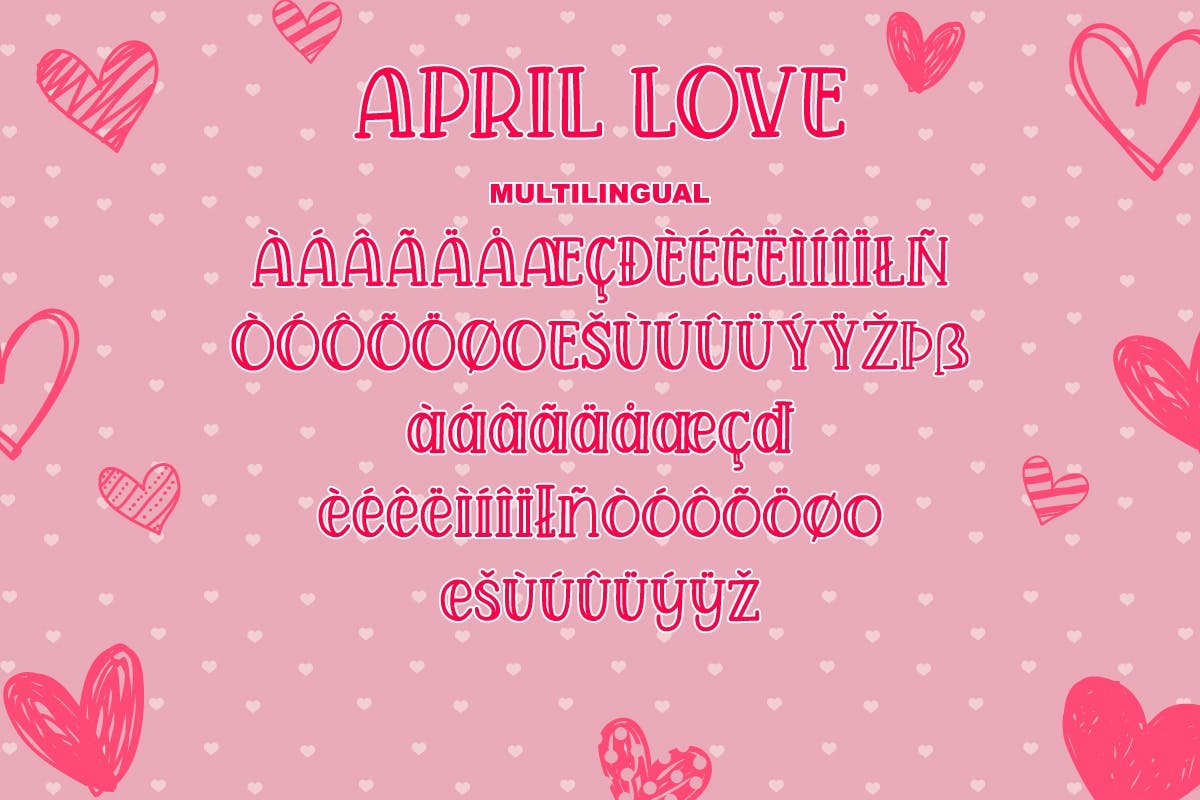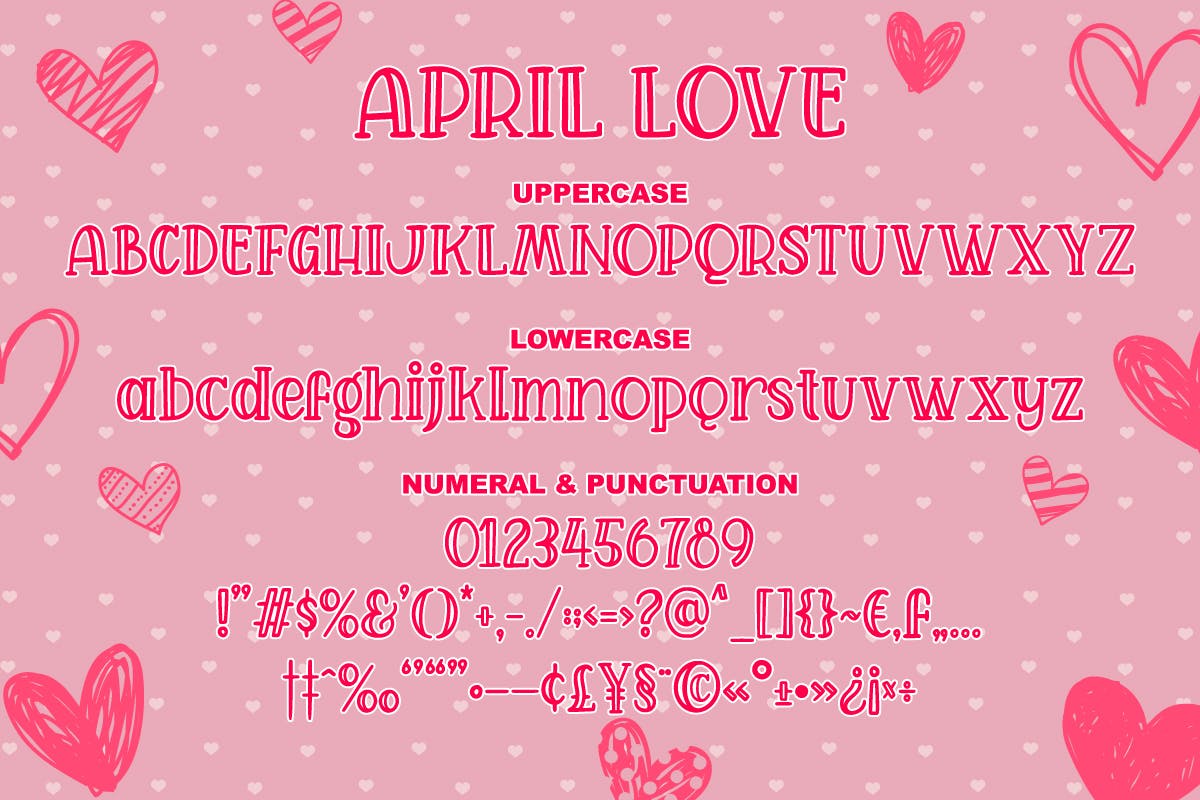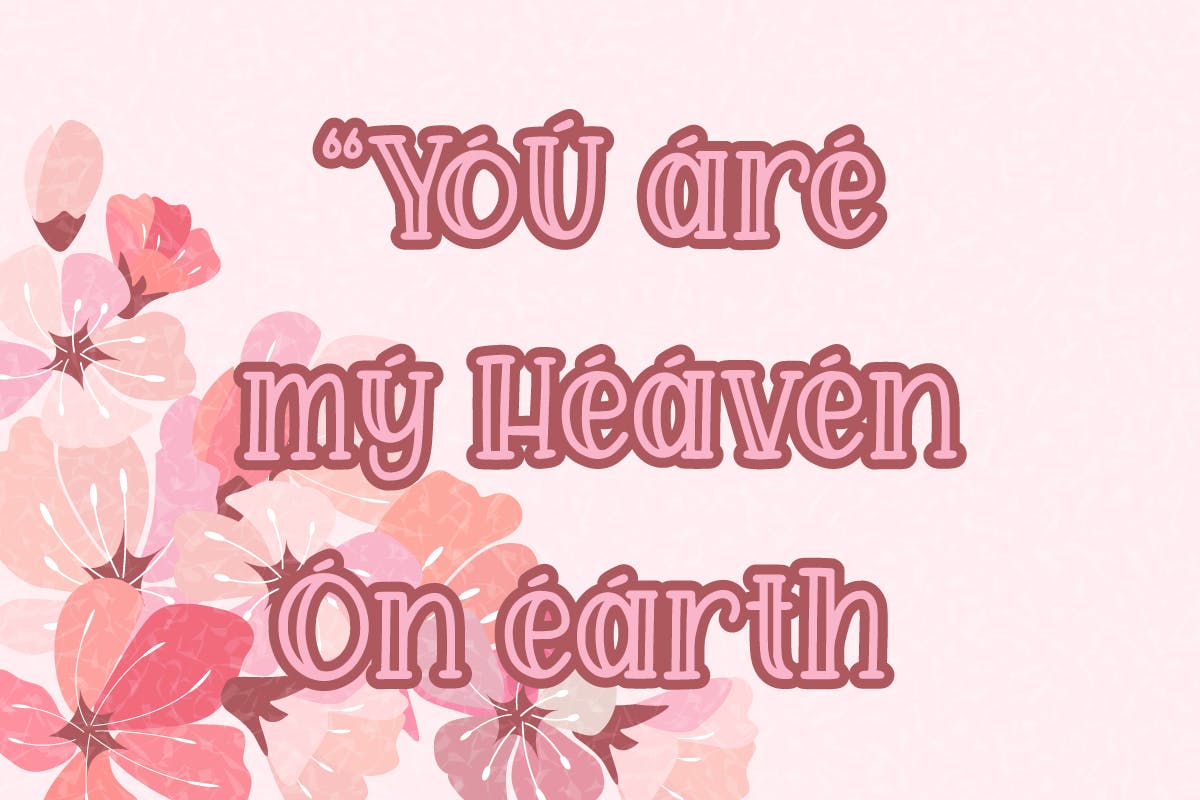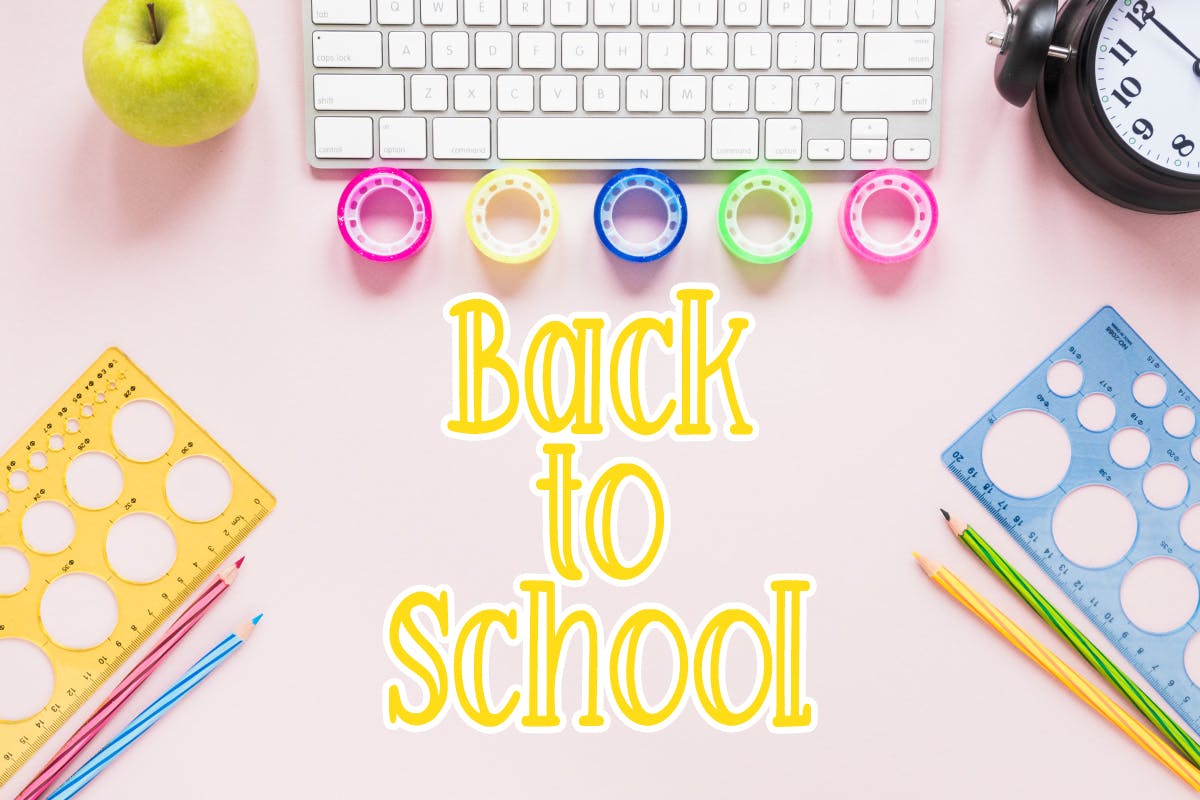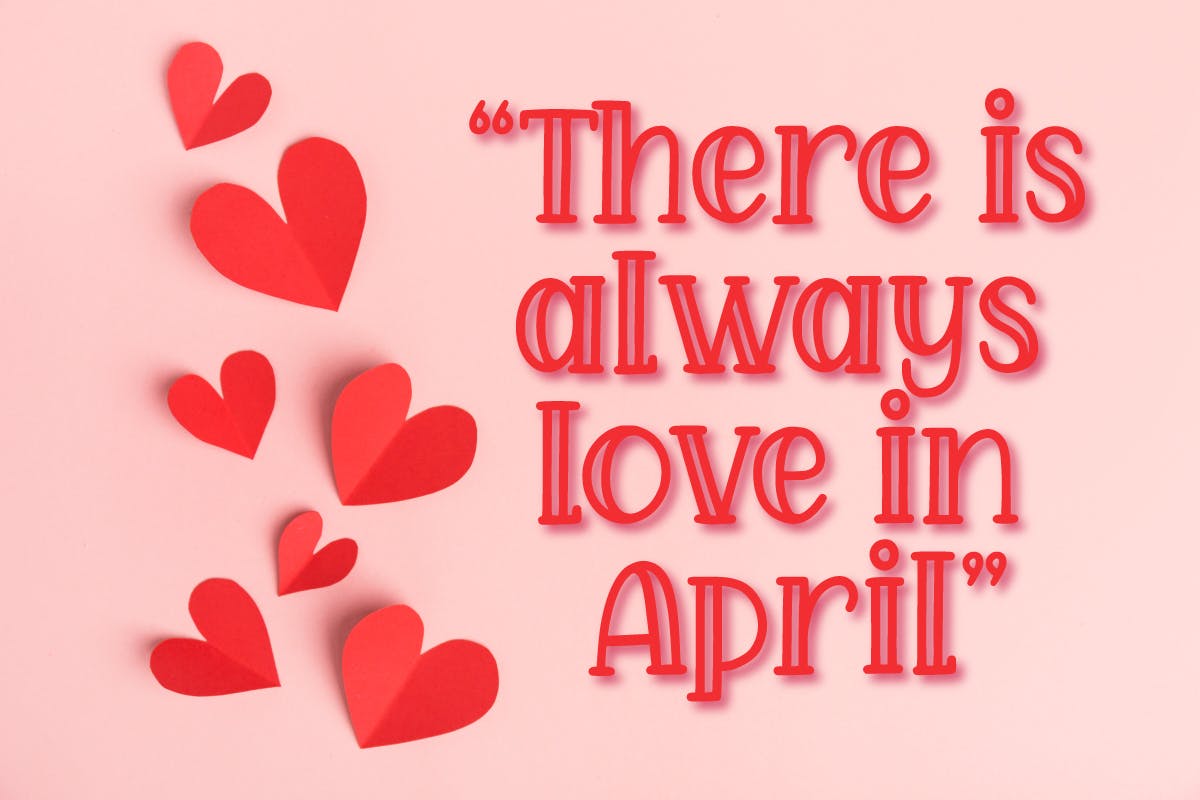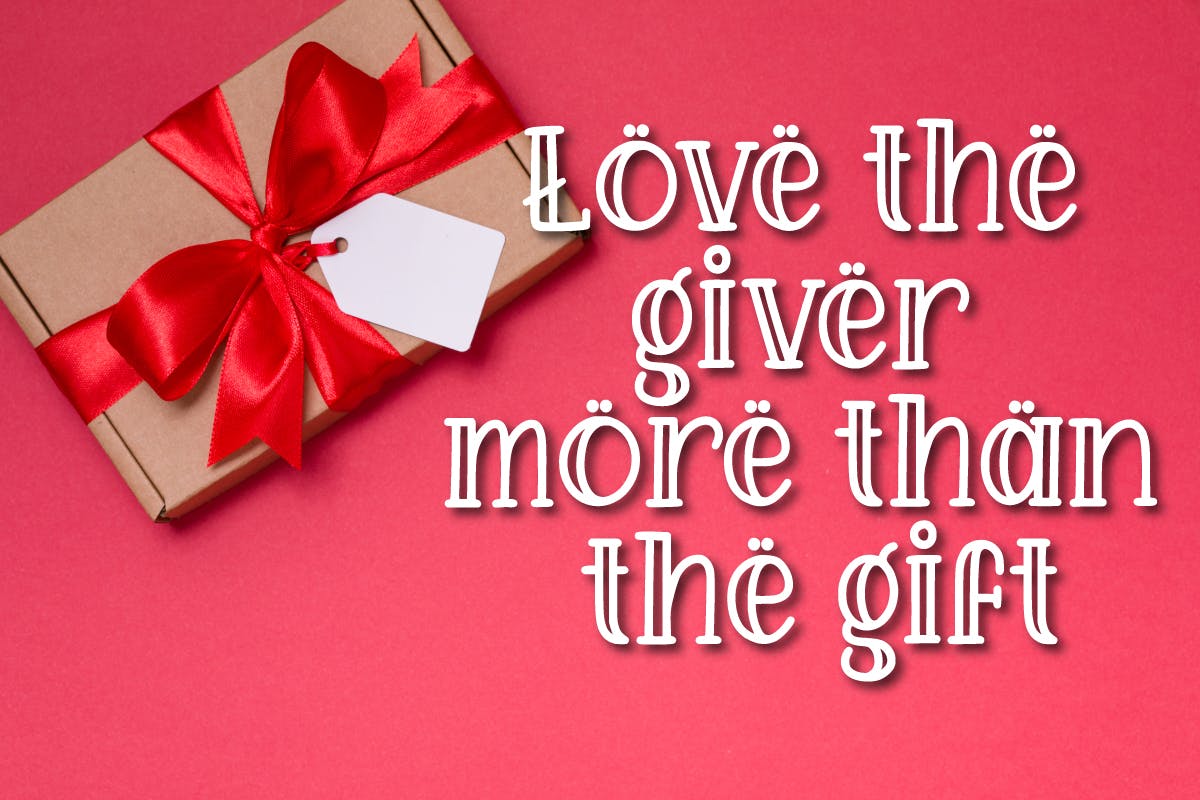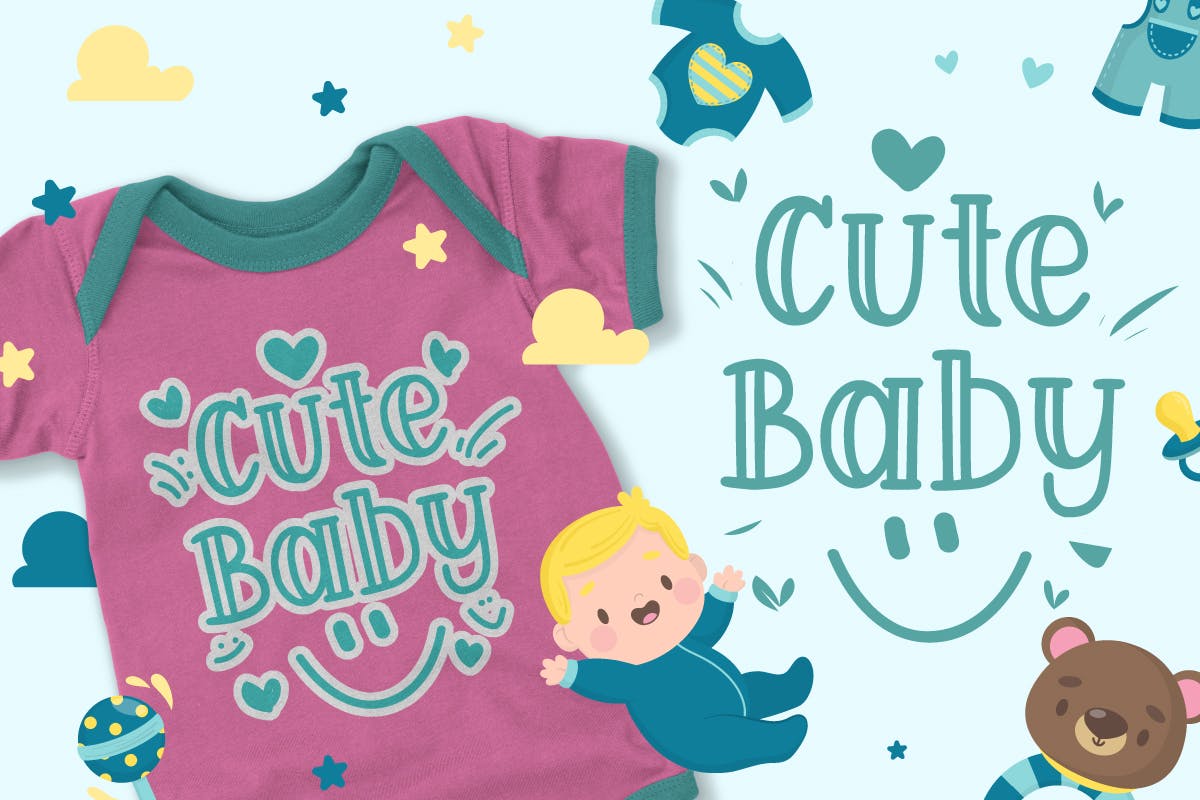
معرفی فونت آوریل لاو - فونت دستساز
فونت آوریل لاو، بهترین انتخاب برای تمام طراحیهای سرگرمکننده شماست. فایل اصلی این فونت شامل کاراکترهای معمولی میباشد و تمام جزئیات با قلم خلاقانه طراحی شده است. بنابراین میتوانید مطمئن باشید که همه اجزا به خوبی با هم هماهنگ میشوند! این فونت برای طراحی تیشرت، نقل قول، برچسب، بستهبندی، لوگو و نوشتار طولانی مناسب است. زیرا ما کرنینگ و ماتریسهایی را برای نیازهای شما تنظیم کردهایم.